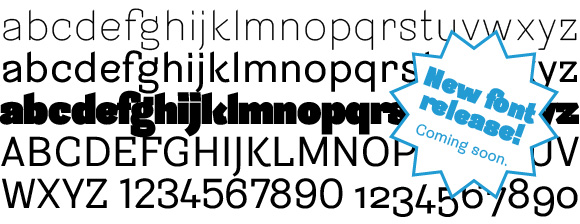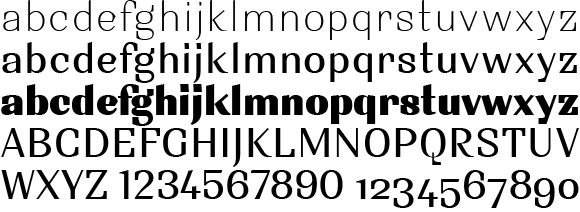
Die Schriftsippe Sintesi wächst. Die Neuerscheinung braucht ein Name. Deine Hilfe wir
Die Neuerscheinung bei der Schriftsippe Sintesi
Die bestehende Schrift Sintesi
Anders als bei der üblichen Konstellation einer Schriftsippe, gehören streng genommen sowohl Sintesi wie auch die Neuerscheinung zur Kategorie der Semi-Serif. Doch unterschiedlicher könnten sie nicht sein: Während Sintesi mit ihrer traditionellen Formen und dem spürbaren Federduktus überrascht, punktet Sintesi Nuova mit robuste, zeitgemäße Formen.
Welcher Name beschreibt am besten diese Konstellation?
Die neue Schriftfamilie heisst Sintesi SemiSans.